What have the Romans ever done for us? 字母設計的起源與演變
羅馬人給我們留下了許多偉大的發明,其中最重要的一項是拉丁字母(羅馬字母)。這種字母是從希臘字母演變而來,最著名的例子就是公元113年完成的圖拉真紀念柱底座上的銘文。隨著羅馬帝國的衰落,這種字型逐漸演變成了不同的地區性書寫體系。
Renaissance influencers 文藝復興時期的變革
14世紀起,人文主義者在義大利佛羅倫薩重新發掘了羅馬字母。他們認為古希臘羅馬時期是一個黃金時代,致力於復興古典文化。他們希望用羅馬風格取代哥特式書寫體,就像用古典建築替代中世紀建築一樣。
15世紀印刷術興起時,大多數書籍都使用哥特體印刷。只有少數古典作品使用羅馬字型。有趣的是,即使在人文主義發源地義大利,羅馬字型也主要用於印刷古羅馬作品。
到了16世紀,特別是1530年代以後,印刷品開始從哥特體轉向羅馬字型。這種轉變很大程度上要歸功於當時人文主義者的影響力。
Garamont and Co. 加蒙德與法國字型的興起
15世紀末,義大利半島是歐洲最重要的印刷中心和字型供應地。但從1530年代開始,法國逐漸成為了字型設計和製作的新中心。這一變化主要歸功於兩個原因:
首先,法國成為了重要的經濟和印刷中心。其次,特別是在巴黎,印刷商開始嘗試用羅馬字型印刷一些傳統上使用哥特體的書籍,如祈禱書等。
在人文學者傑弗裡·托里和法國宮廷的推動下,羅馬字型的使用越來越廣泛。為了滿足這種需求,一批新的字型設計師應運而生,其中最著名的包括克勞德·加蒙德(又寫作加拉蒙)等人。
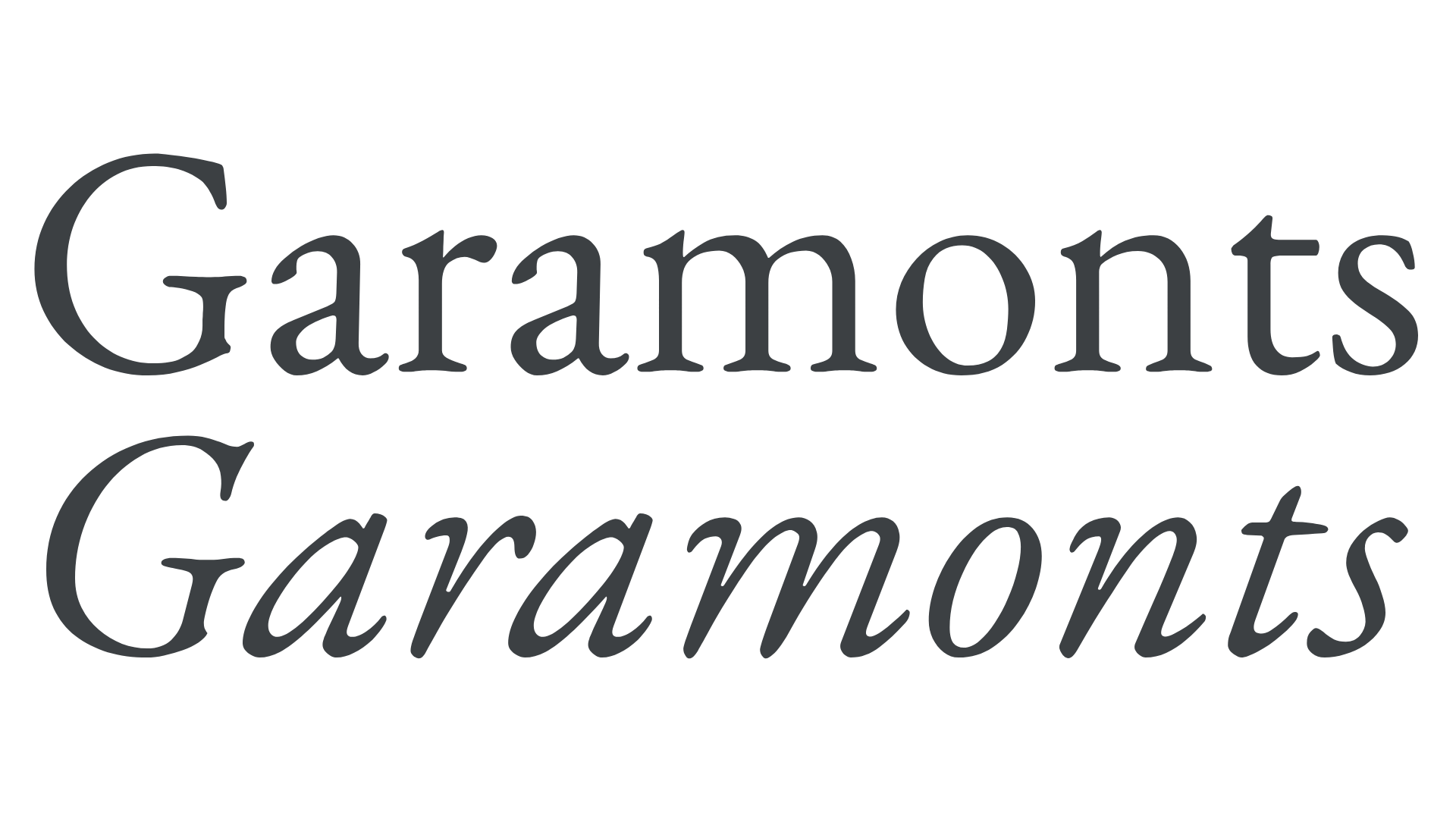
加蒙德和他的同時代人設計的字型很快取代了義大利的字型風格。這些新的法國文藝復興風格字型特點是筆畫對比更強,字距更寬鬆,整體看起來更輕盈、典雅,與哥特體的厚重風格形成鮮明對比。
Inventing italic 斜體字的誕生與發展
16世紀,威尼斯印刷家阿爾杜斯·馬努提烏斯委託設計師弗朗切斯科·格里福創造了一種新字型,用於印刷小開本書籍。這種字型基於人文主義者使用的一種草書風格,後來被稱為斜體字(義大利體)。
斜體字最初是為了讓書籍看起來更隨意、更易讀。它最早與直立的羅馬大寫字母搭配使用,後來發展出了配套的傾斜大寫字母。
如今,斜體字主要用作輔助角色,常用於強調文字、外來語、引用和書籍標題等場合。它不再用來排印整本書,而是成為了一種重要的文字變體形式。